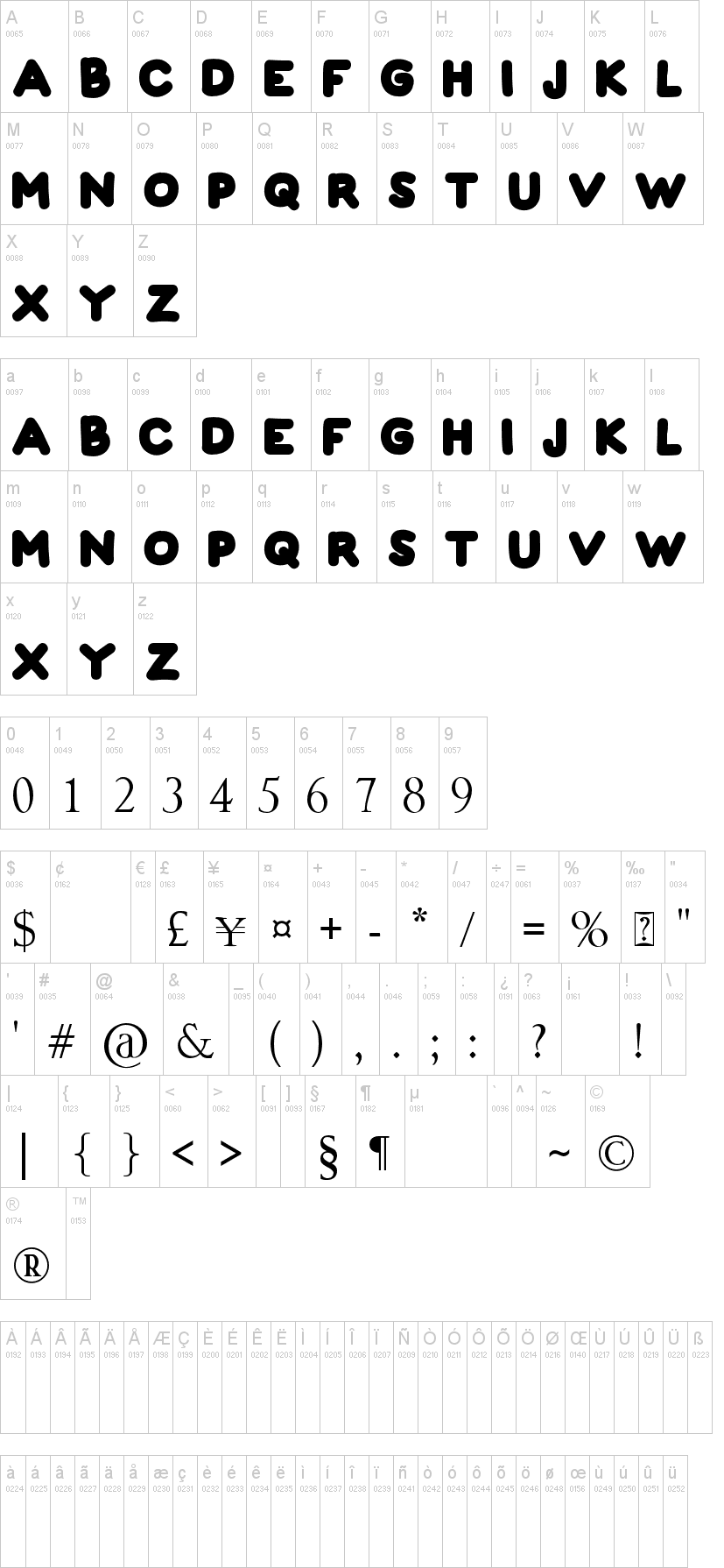
Florian
Florian 字体是一种现代风格的无衬线字体,由设计师 Florian Karsten 创造。它的设计灵感来自于德国包豪斯风格,强调了简单、几何化的形状和清晰的线条。Florian 字体的特点是字母形态的简化,但仍然保持了可读性,因此适合于任何应用场景,从印刷品到数字设计,都能发挥出色。此外,Florian 字体家族包含多种字重和风格,使得它在设计中的灵活性更高。
Florian是一款非常不错的手写艺术字体,具有很好的视觉感,适合于文化类的宣传设计、商业类品牌的广告和产品包装设计以及个性化文字排版等较多场景。
Florian字符映射图